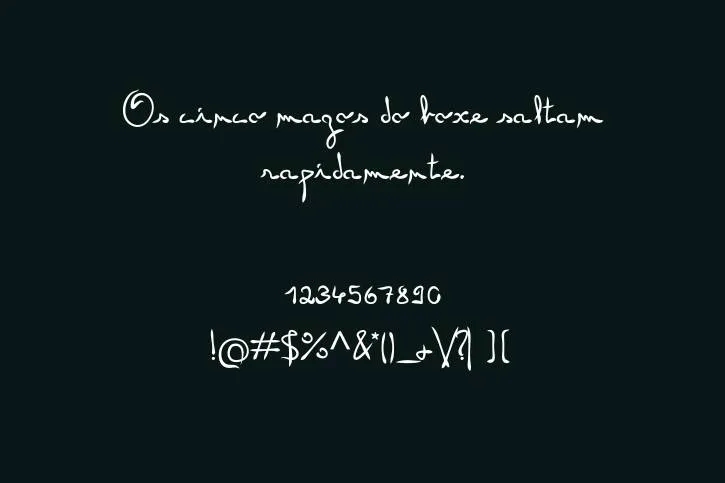
A fonte Angel Light é uma tipografia delicada e elegante que incorpora uma estética suave e celestial. É uma fonte de caligrafia desenhada por Rémi Godefroid. Com linhas finas e curvas graciosas, esta fonte transmite uma sensação de leveza e serenidade. Inspirado na caligrafia manual, oferece uma expressão tipográfica requintada e acolhedora.
Seu design diferenciado se destaca pela graciosidade e simplicidade. Esta fonte de aparência moderna é adequada para combinar com a Fonte Vegan Style, que também é uma fonte semelhante. Cada personagem é cuidadosamente desenhado para refletir a suavidade e elegância desejadas, proporcionando uma aparência coesa e harmoniosa. Sua beleza está na simplicidade dos personagens, o que resulta em uma tipografia ideal para projetos que buscam uma atmosfera celestial e sofisticada.
A sua versatilidade é evidente na sua capacidade de integração com diferentes estilos de design. Seja em projetos digitais que exigem presença refinada ou em materiais impressos que buscam transmitir um charme clássico, a fonte mantém sua elegância e legibilidade. Suas variações estilísticas oferecem opções de personalização de composições tipográficas, proporcionando flexibilidade criativa aos designers.
Fonte Angel Light Integração Perfeita
Oferece perfeita integração em diversos projetos de design, caracterizando-se pela sua versatilidade e capacidade de adaptação a diferentes contextos visuais. Esta integração harmoniosa é o resultado de vários fatores que a destacam como uma escolha ideal:
Leveza e Versatilidade: Sua delicadeza intrínseca o torna versátil, permitindo sua fácil integração em designs que buscam um ambiente leve e elegante.
Design Neutro e Sofisticado: Seu design neutro e sofisticado permite sua utilização nas mais diversas aplicações, desde convites formais até materiais promocionais e digitais.
Compatibilidade Estilística: É compatível com uma variedade de estilos visuais, do tradicional ao contemporâneo. O designer pode facilmente combiná-lo com a fonte Maya, que é uma fonte manuscrita de aparência arrojada.
Suavidade e Elegância: A suavidade e elegância dos seus personagens garantem uma integração que transmite uma sensação de requinte.
Aplicativos que Usam a Fonte Angel Light
- Convites de festas infantis.
- Cartões de aniversário e saudações.
- Materiais escolares e educativos.
- Embalagens de produtos relacionados a confeitaria.
- Postagens em redes sociais com temáticas lúdicas.
- Criação de logotipos para negócios criativos.
- Decoração de festas e eventos temáticos.
- Projetos de artesanato e DIY.
- Páginas de scrapbook e álbuns de memórias.
- Elementos gráficos em websites e blogs divertidos.
Que tipo de fonte é a fonte Angel Light?
É uma fonte de caligrafia desenhada por Rémi Godefroid, com linhas finas e curvas graciosas.
Qual é a melhor característica desta fonte?
Sua melhor característica está no design delicado e elegante, conferindo uma sensação de graça celestial e sofisticação às composições visuais.
Qual é o melhor uso da fonte Angel Light?
É mais adequado para projetos elegantes e refinados, como convites de casamento, materiais para eventos formais e designs que exigem um toque de charme celestial.